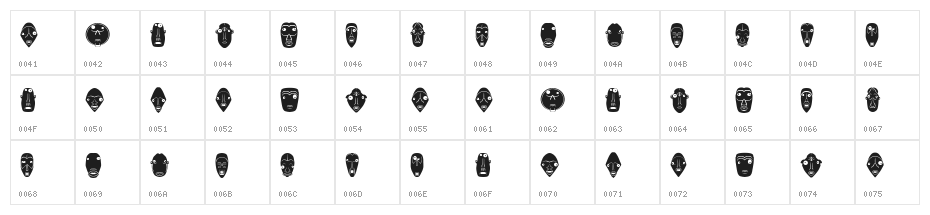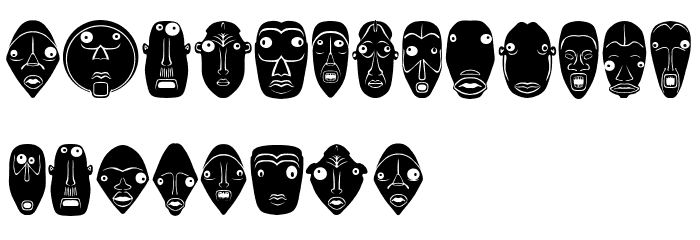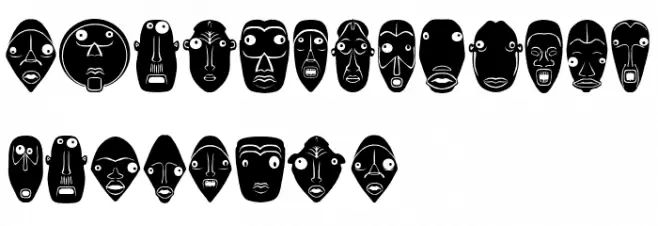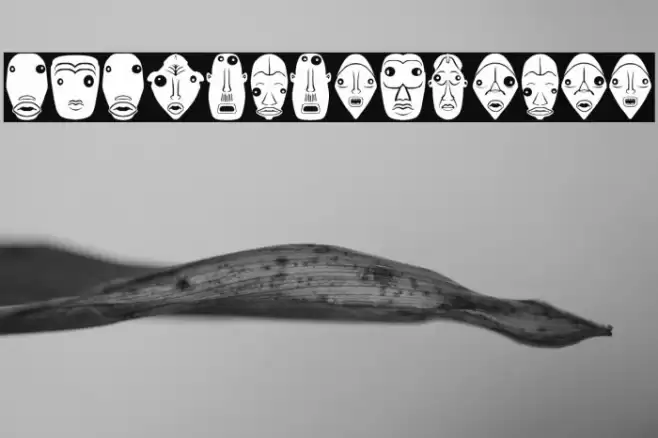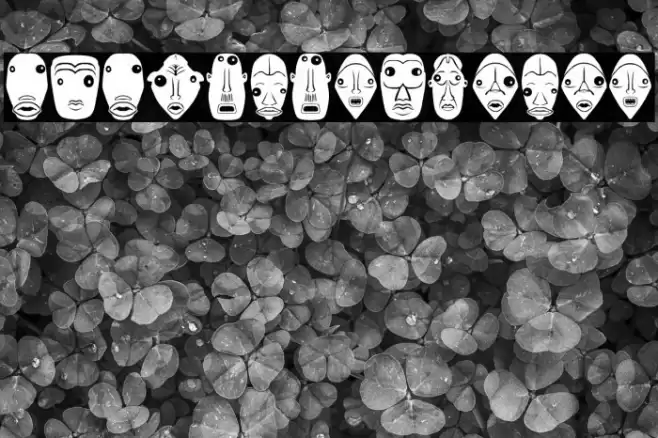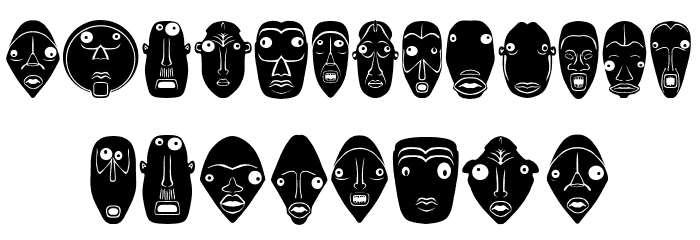
Isitolo Regular Font
| Общий стиль | Decorative, Playful, Artistic, Ethnic-inspired |
| Область применения | Logos, Posters, Headlines, Artistic projects |
| Рекомендуемые проекты | Children’s books, posters, album covers, cultural event branding, art installations. |